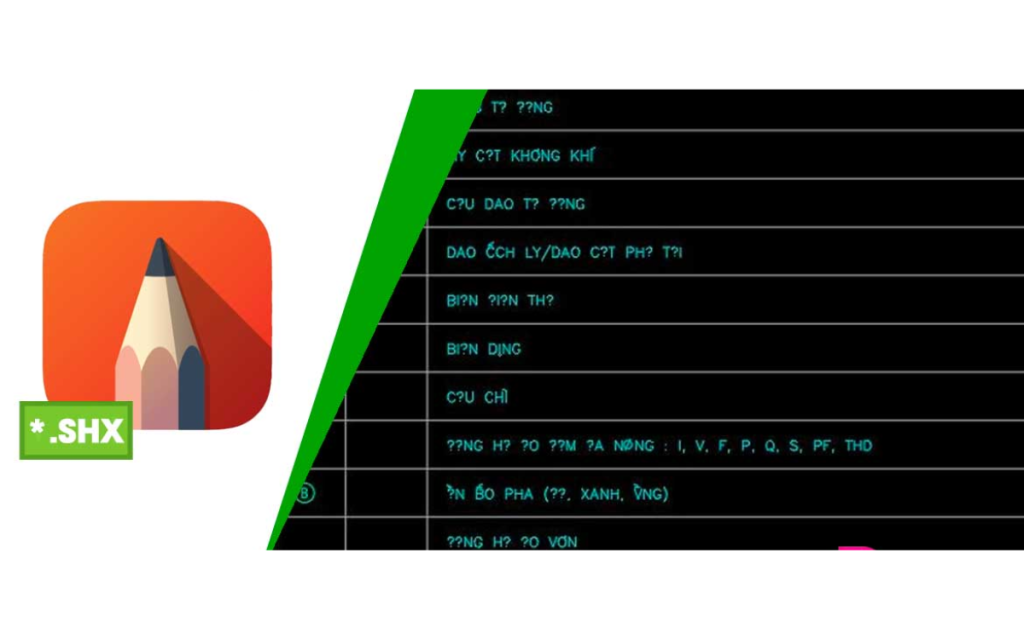
Font Vnsimli Shx
Tác giả: vietfontz.com
Việt hóa: Không rõ
Bộ Font: Font VNSimli SHX
Phân loại: Kỹ thuật
Kiểu chữ: SHX (dùng cho AutoCAD)
Font Vnsimli Shx là một font chữ đặc trưng được sử dụng phổ biến trong phần mềm AutoCAD và các ứng dụng thiết kế kỹ thuật khác tại Việt Nam. Đây là một font chữ có hỗ trợ tiếng Việt, được thiết kế theo chuẩn SHX, giúp đảm bảo tính tương thích cao với các bản vẽ kỹ thuật. Font “VNSimli SHX” thuộc bộ font chữ không chân, nổi bật với các đường nét đơn giản, rõ ràng, giúp các ký tự dễ dàng đọc được trên các bản vẽ có nhiều chi tiết. Đây là sự lựa chọn tối ưu cho các kiến trúc sư, kỹ sư và nhà thiết kế khi cần thể hiện nội dung văn bản trên các bản vẽ kỹ thuật số.